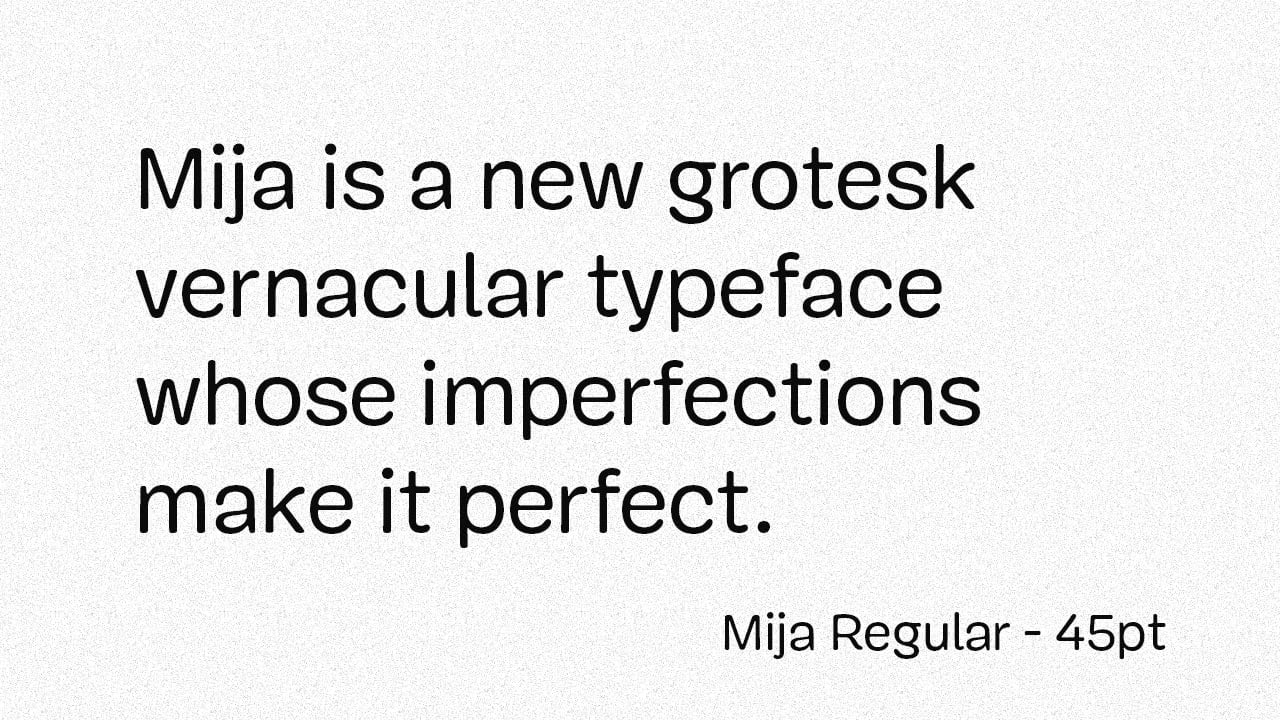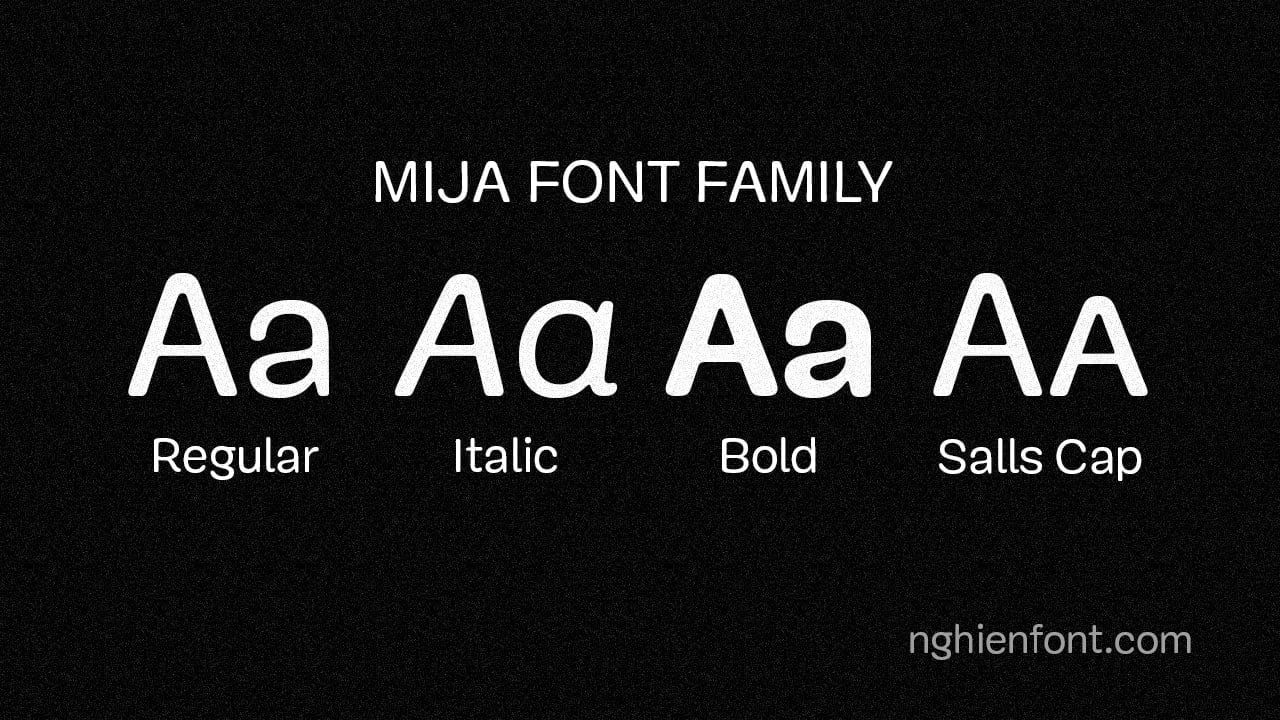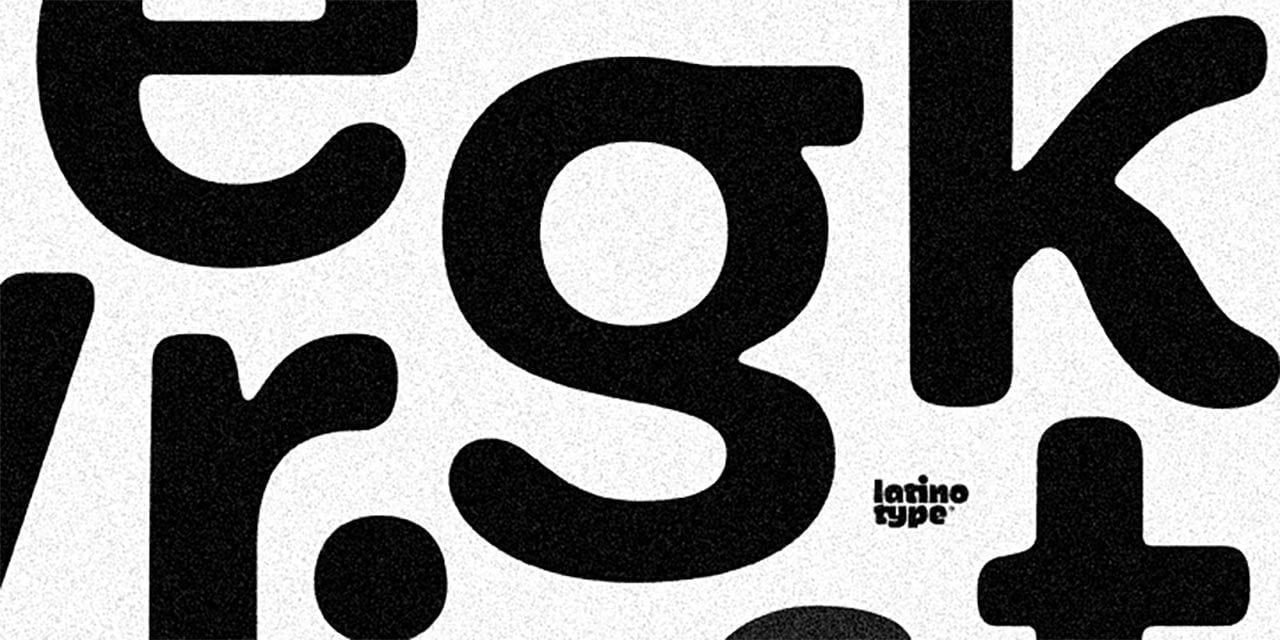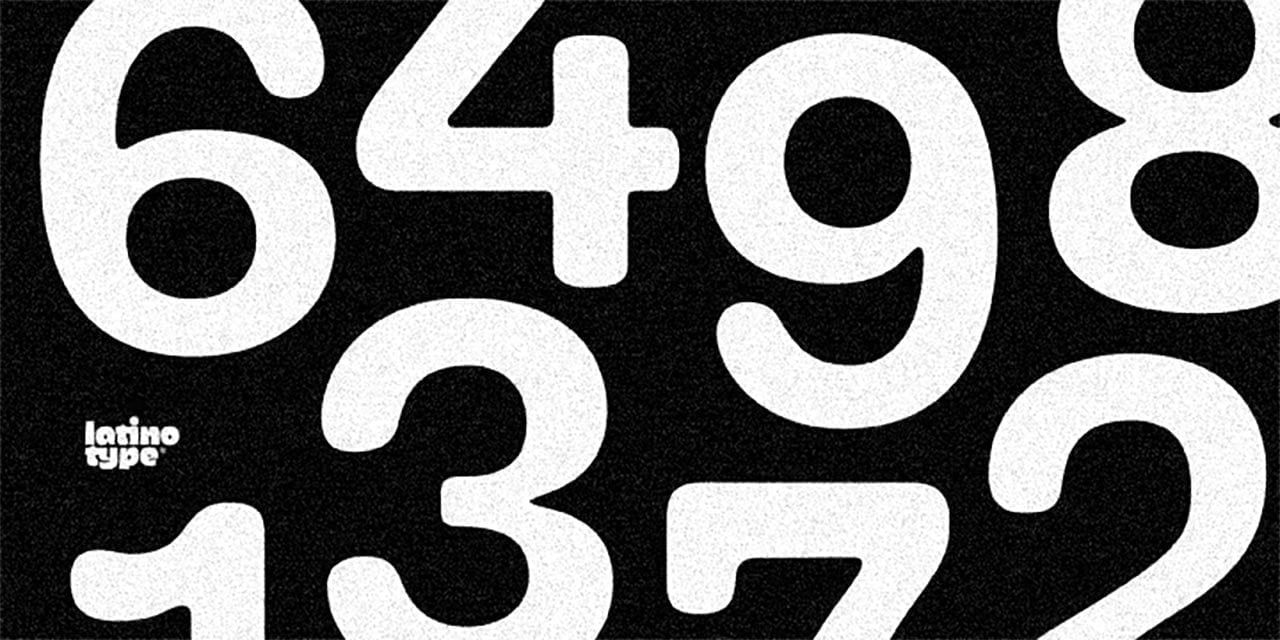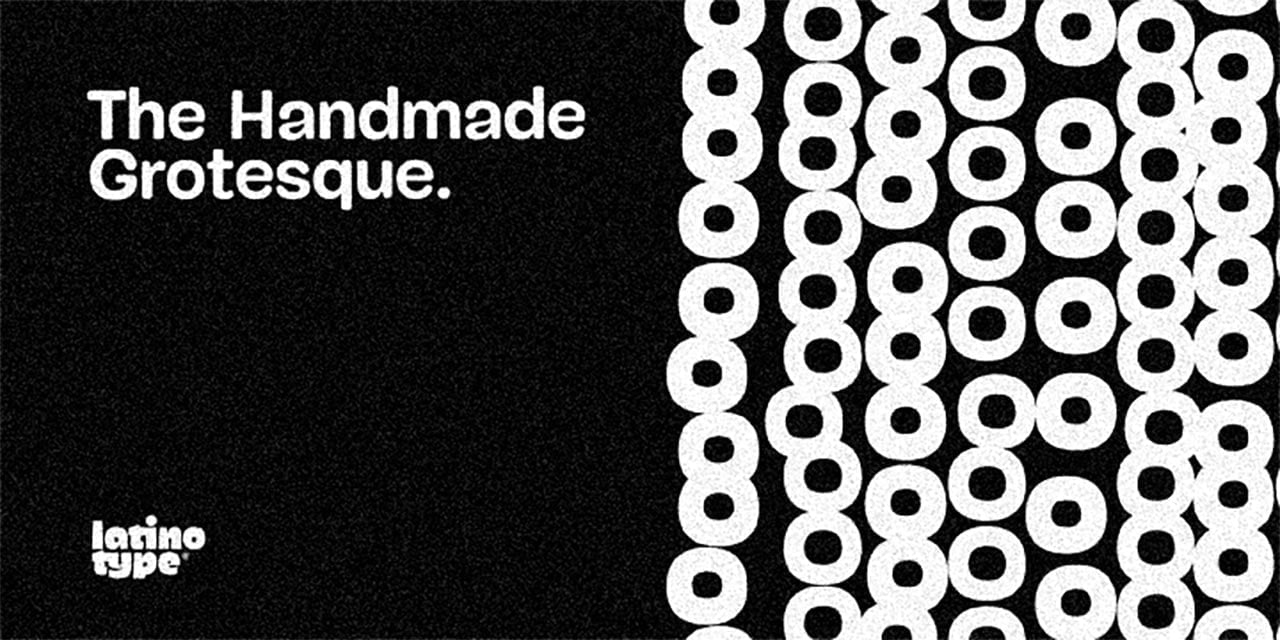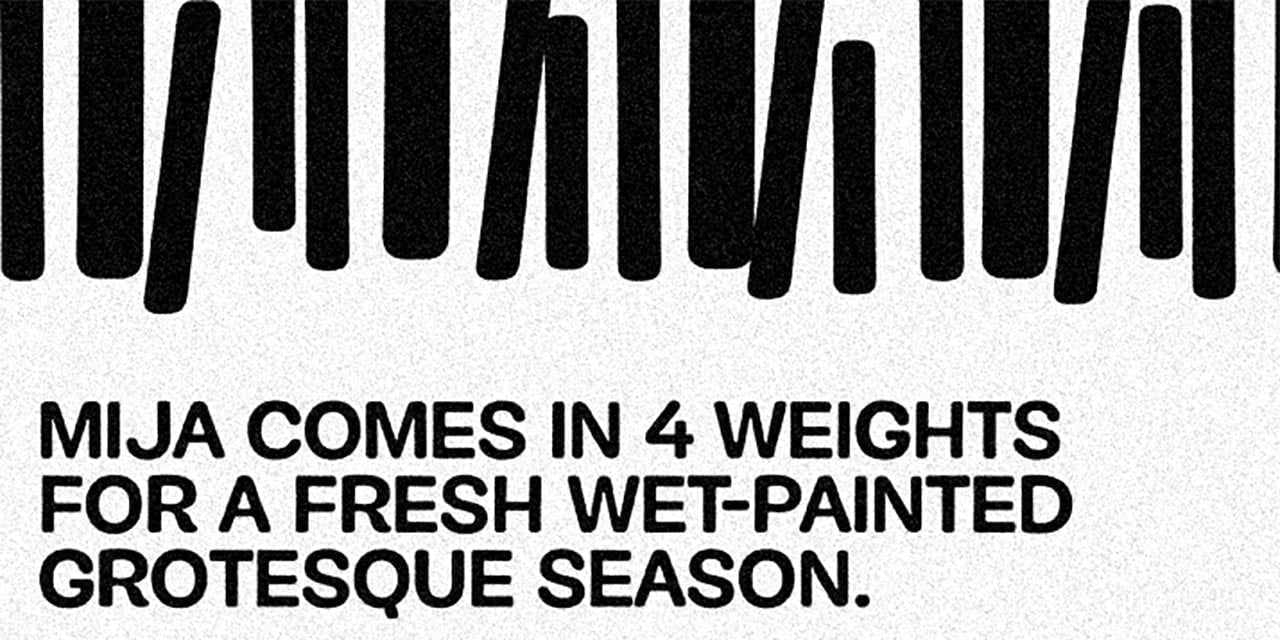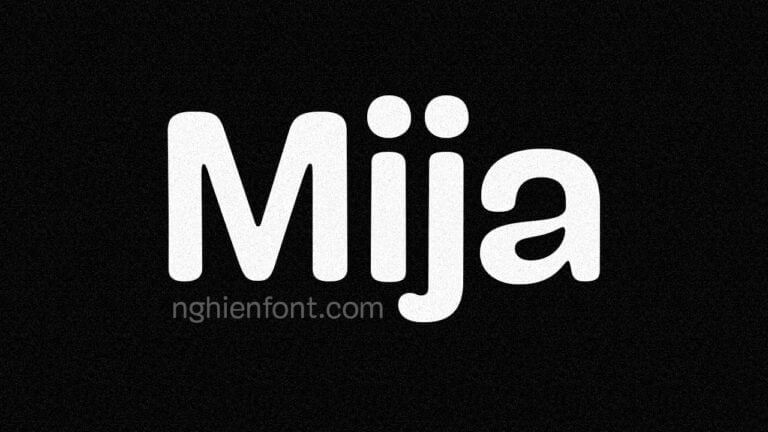
Mija là một kiểu chữ được làm thủ công theo phong cách grotesk. Đây là một kiểu chữ hiển thị với cảm giác ấm áp và mềm mại được vẽ bằng tay. Kiểu chữ này được lấy cảm hứng từ các biển hiệu.
Mija hiển thị tốt ở cả kích thước lớn và nhỏ. Bộ font này bao gồm 4 kiểu (Roman, Bold, Italic và Small Caps) là một gói combo phù để giải quyết hầu hết các vấn đề văn bản thông thường trong thiết kế đồ họa.
Mija xuất phát từ từ “mi hija” nghĩa đen là “con gái tôi”. Nó là một thuật ngữ thân thiết tiếng Tây Ban Nha thường được sử dụng bởi người lớn đối với một cô gái hoặc phụ nữ trẻ.
Với các nét chữ tròn trịa, mềm mại vì vậy mà bộ font này phù hợp cho rất nhiều thiết kế khác nhau như làm tiêu đề, thiết kế website, trang trí, thiệp mời…
Mija is a sans serif and display sans font family